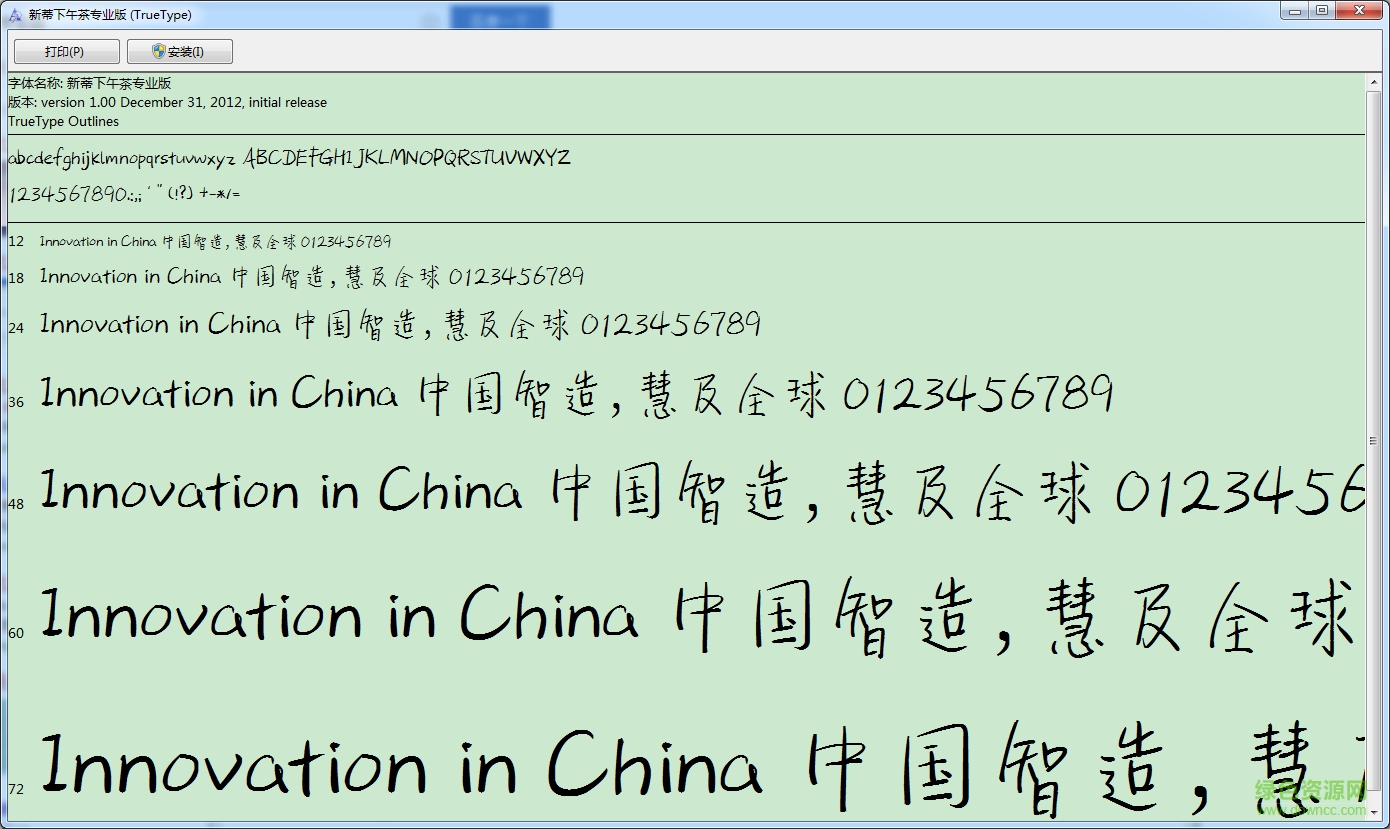
新蒂下午茶专业版是一款极具艺术感性的简体字体,这款字体类似与手写效果,非常适用于书信、消息、艺术设计等方面,需要的朋友可以来绿色资源网免费下载使用!
新蒂下午茶专业版是一款应用于设计方面的简体中文字体,该字体纯属手工输入,字形潇洒大方,效果非常不错,能够应用于签名设计、平面设计、名片设计、广告创意、印刷包装等领域。